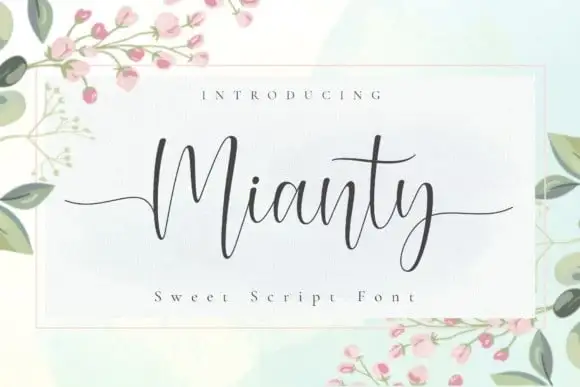
Mianty Calligraphy Font
Olá amantes do design. A Mianty Calligraphy Font é uma linda fonte script que traz à tona seu melhor lado. Com tons de energia e elegância, ela oferece uma fonte perfeita para criar tipos de texto artesanal em apenas alguns cliques. Desenvolvida pelo designer AV Type, a Mianty se torna um tipo fluido e sofisticado que se desdobra à sua vontade. Esta fonte PUA (Personal Use Allowed) proporciona uma experiência tranquila ao aceder a todos os caracteres e swashes de forma intuitiva. Possui linhas suaves e formas belas, além de alternativas magníficas, mantendo fiel ao seu carácter clássico da tipografia calligráfica. Ao mesmo tempo, oferece um toque contemporâneo que certamente fará sua marca. Descubra a paixão pela Mianty Calligraphy Font e inspire seus projetos para níveis mais altos! Este é um atalho perfeito para os entusiastas do design gráfico em busca de uma fonte única e impecável.